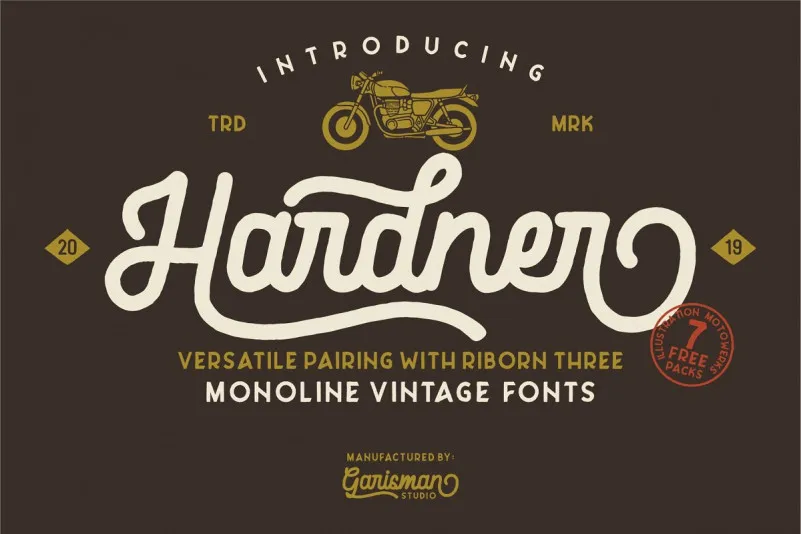
Esta é uma fonte vintage única, criada pela M.0Type, que combina beleza e vintage num pacote atraente. Sua estética moderna e monoline se inspira na elegância dos motociclistas vintage. Introduzindo a Fonte Hardner Vintage, esta é uma tipografia de exibição moderna e vintage, feita à mão que traz um toque inconfundível da era do motor de quatro tempos. Além disso, o conjunto inclui a fonte RIBORN Three, gratuita em sua compra deste produto. Seja para nomes de empresas, logomarcas ou qualquer outro uso que exija um estilo vintage moderno e sofisticado, esta é uma escolha perfeita.